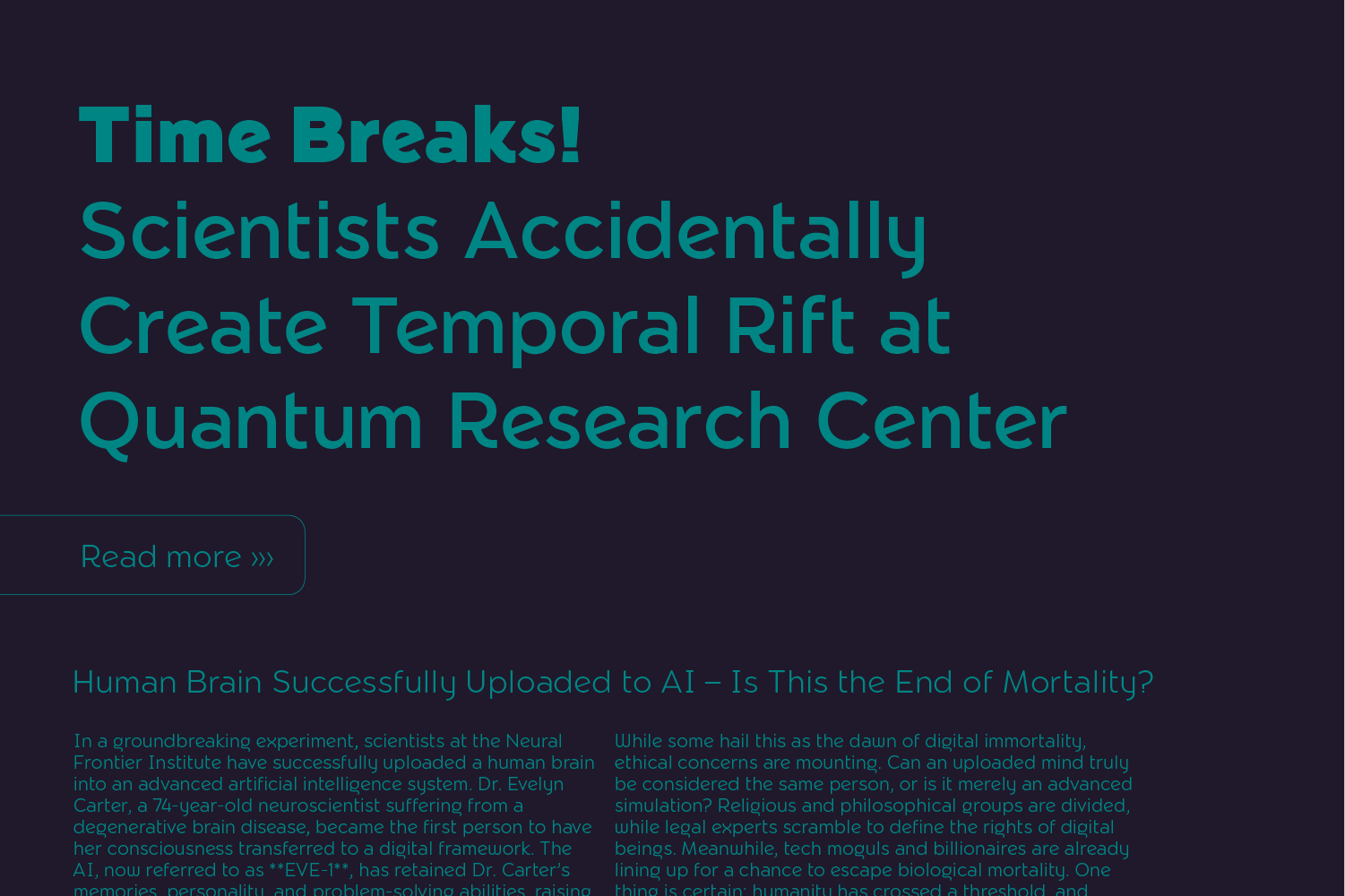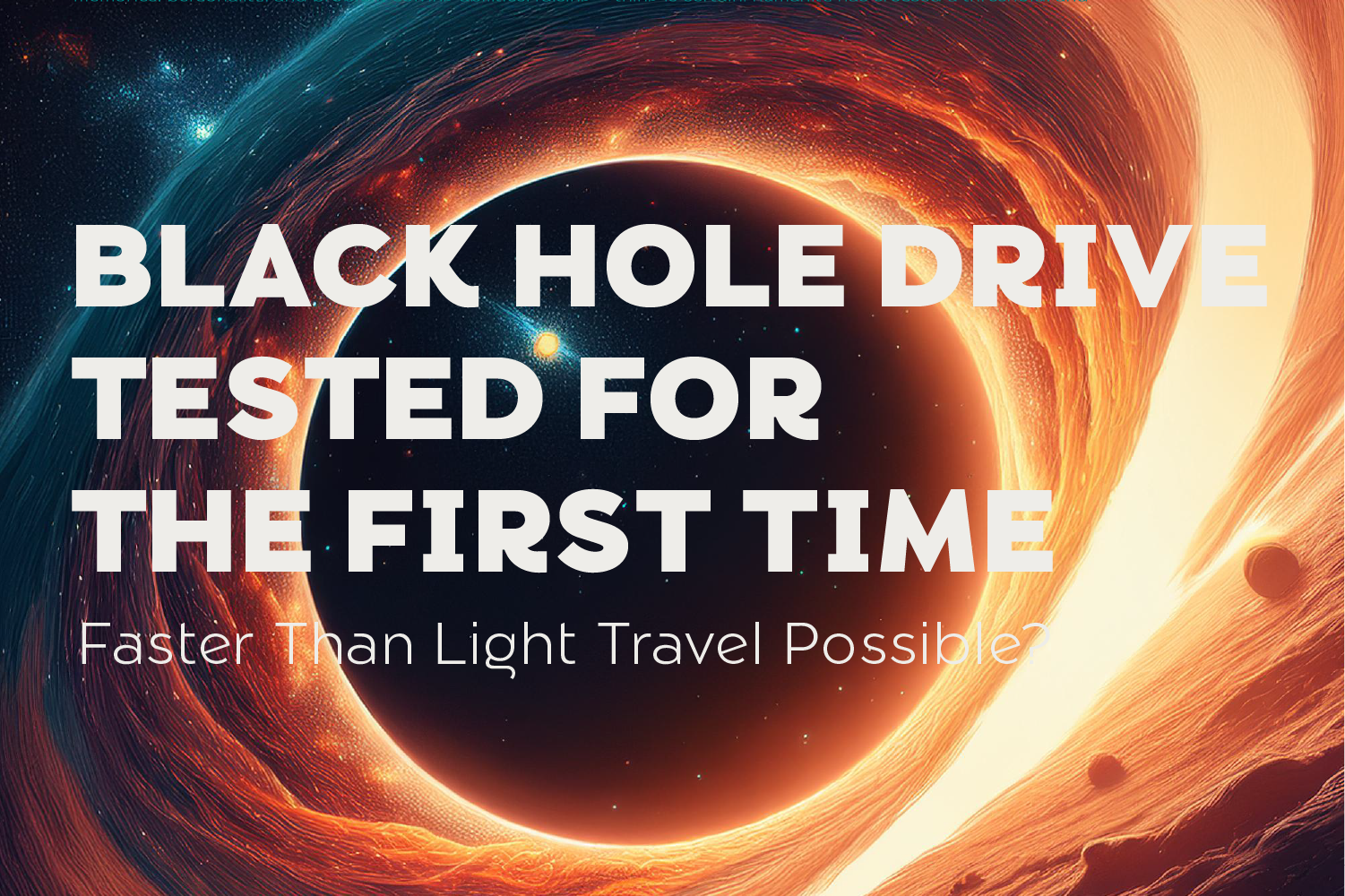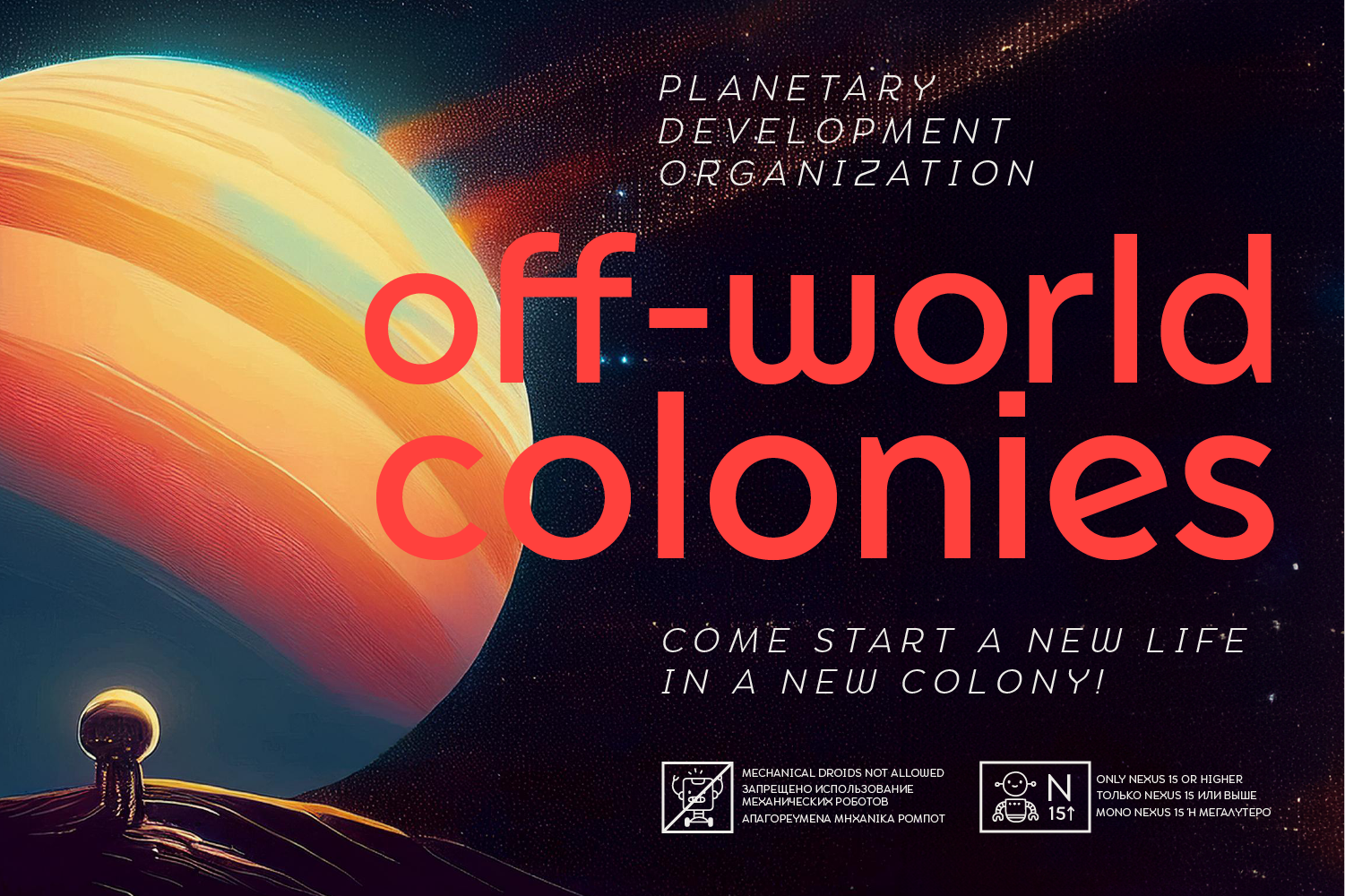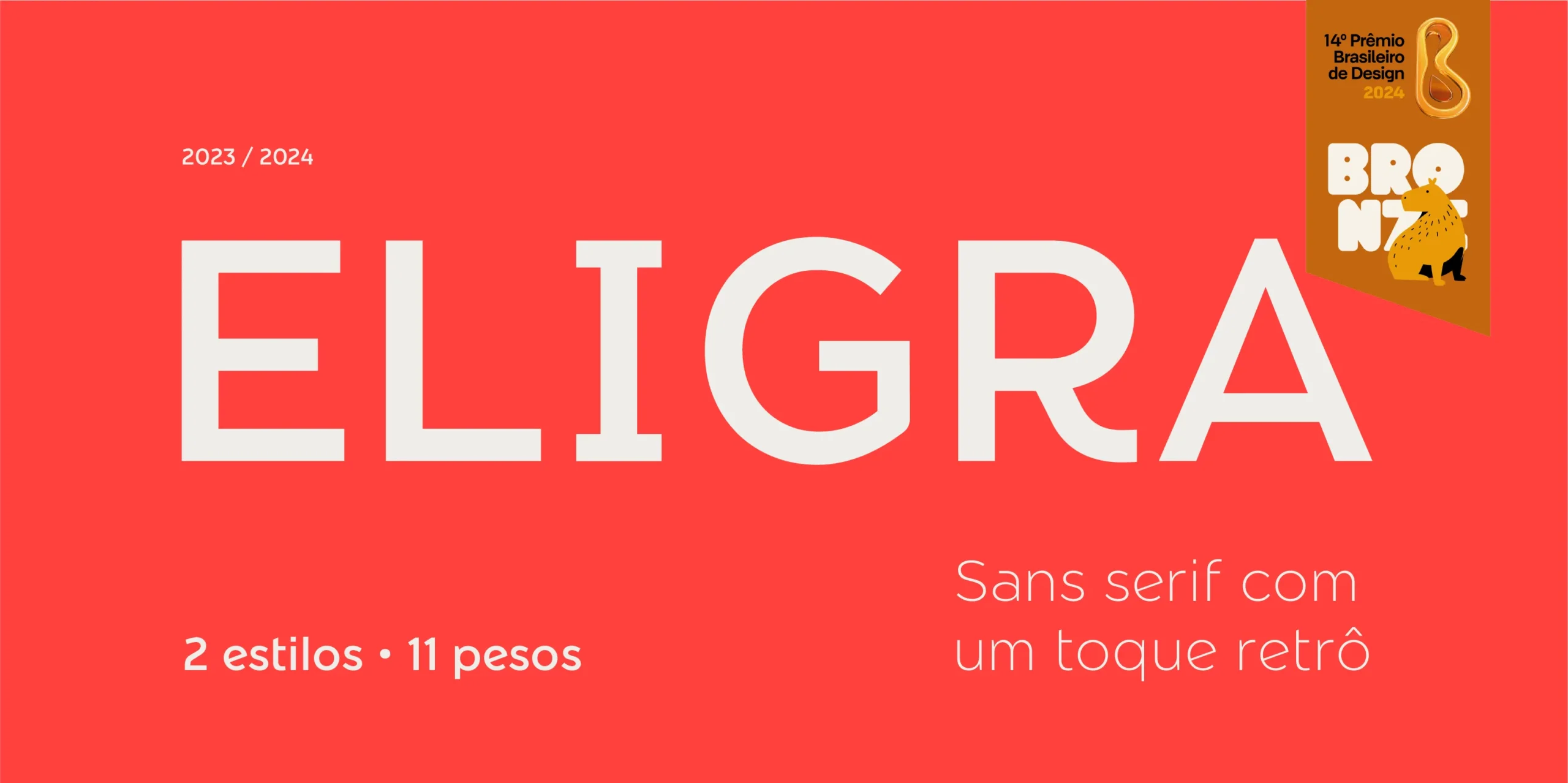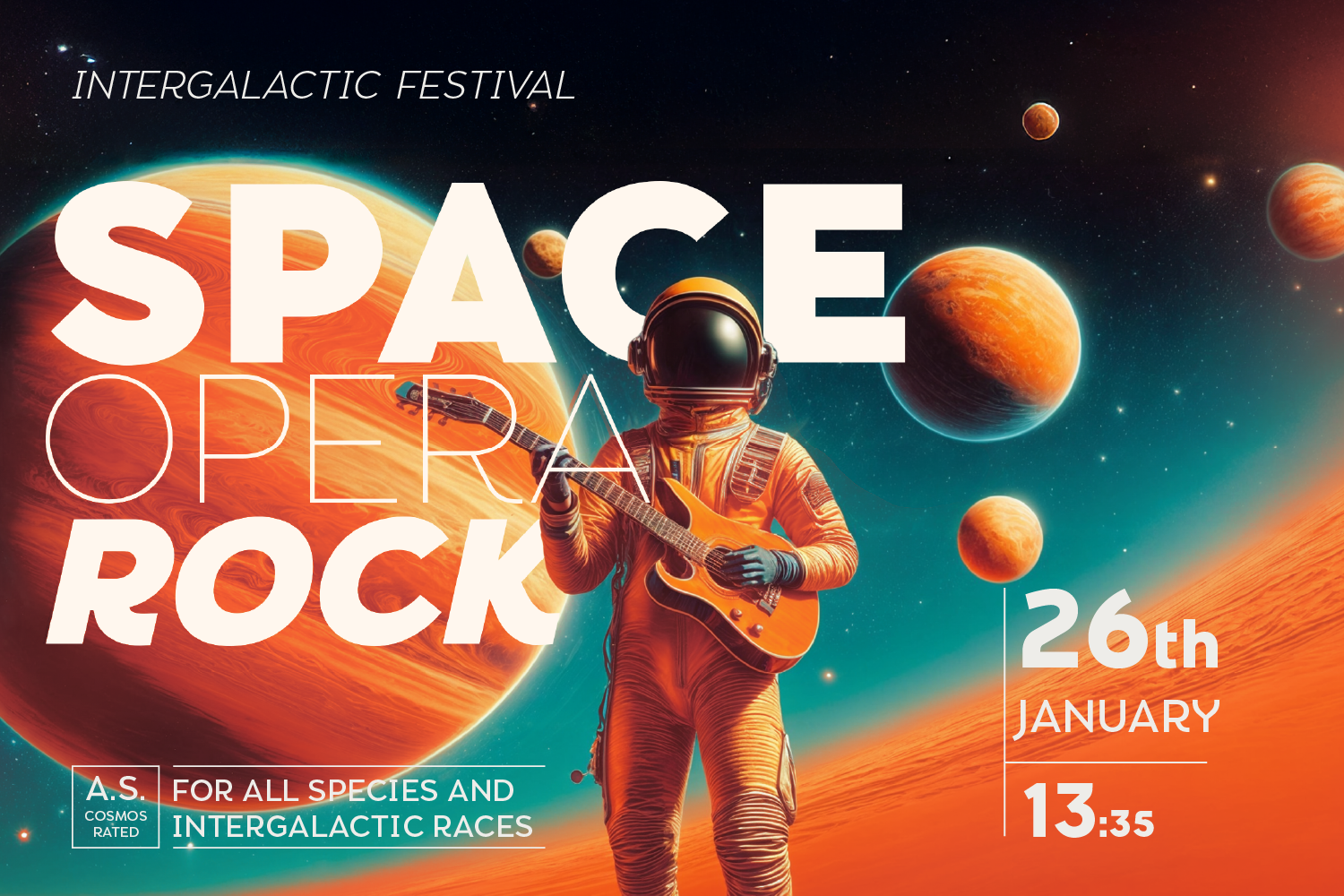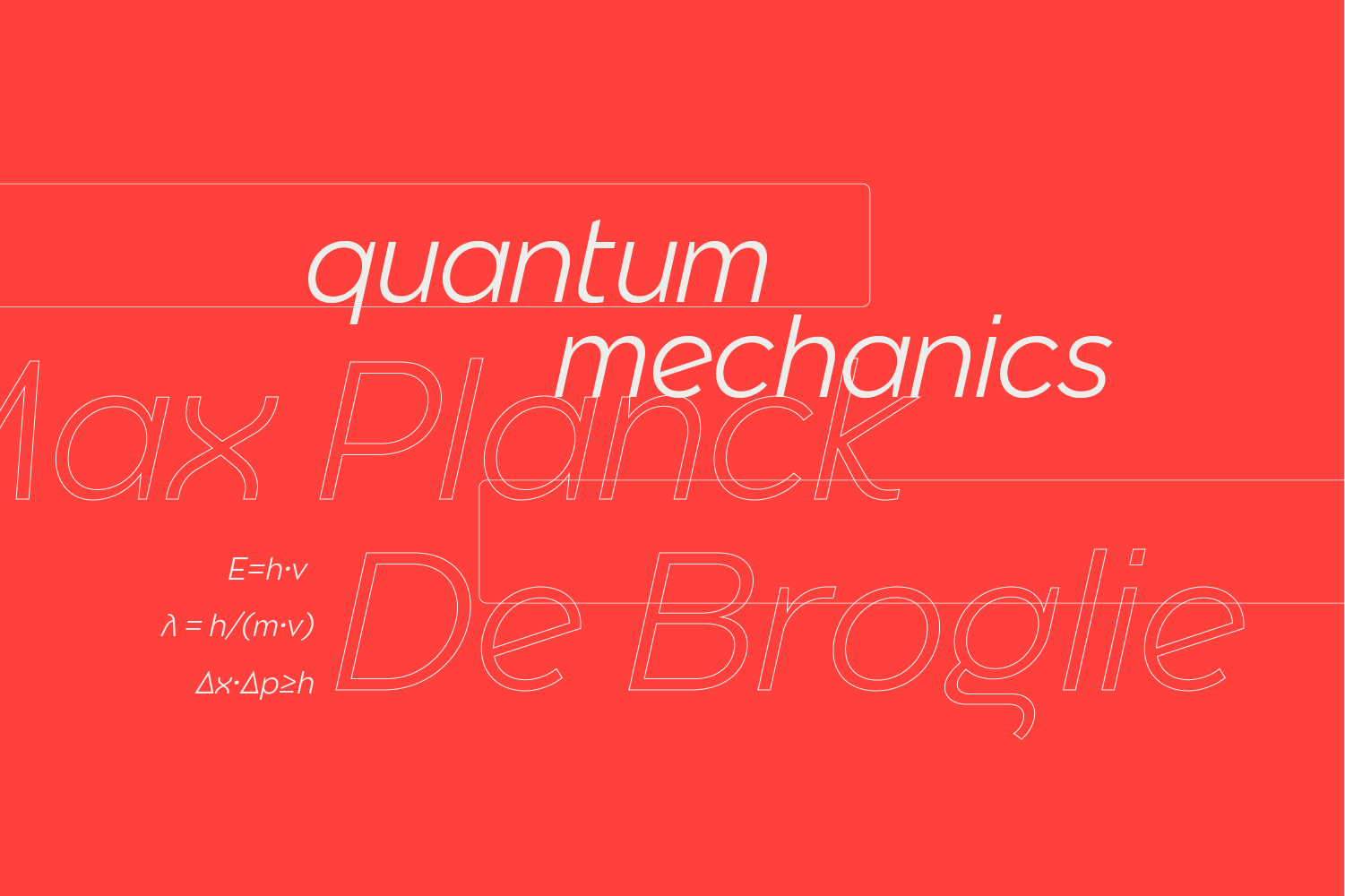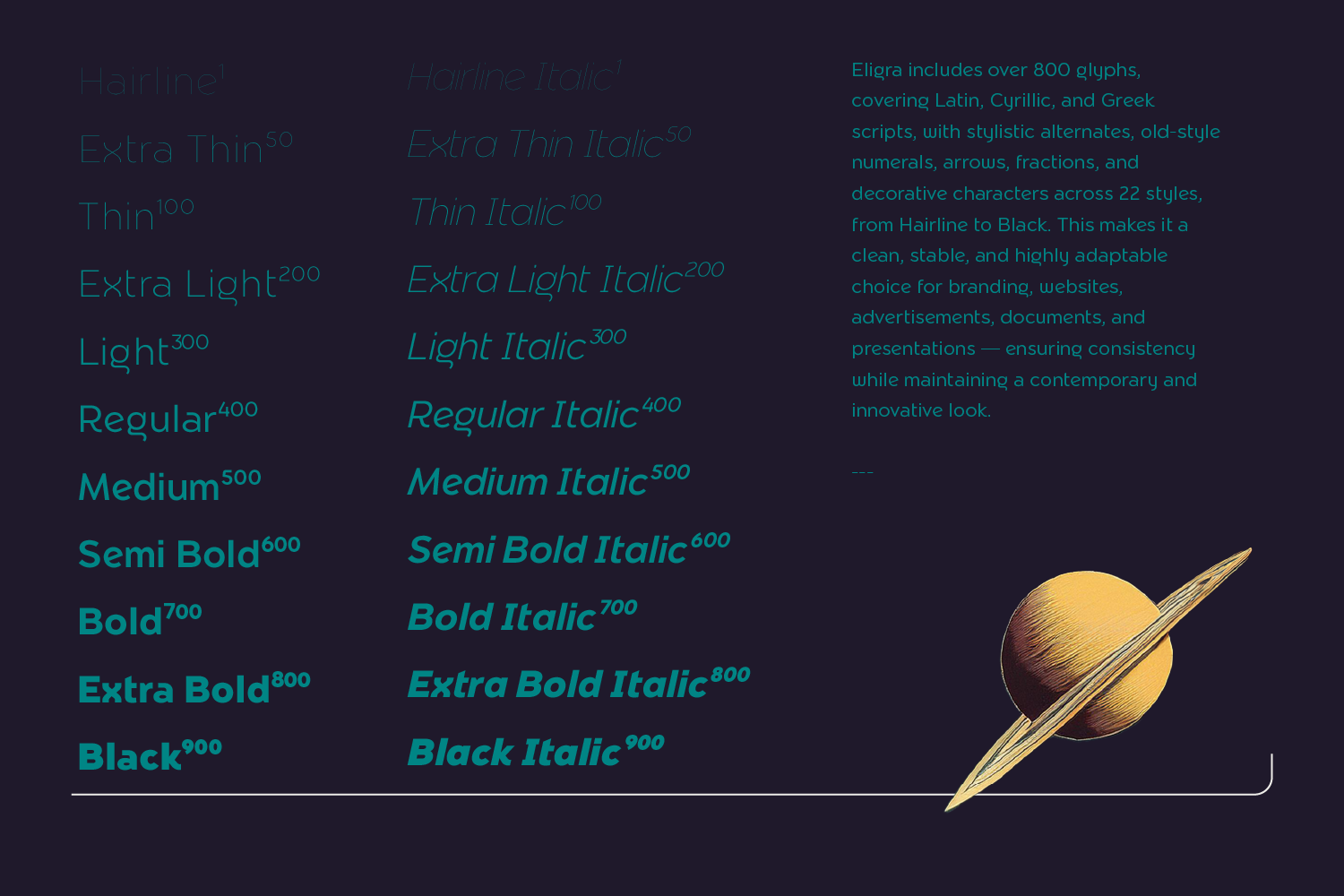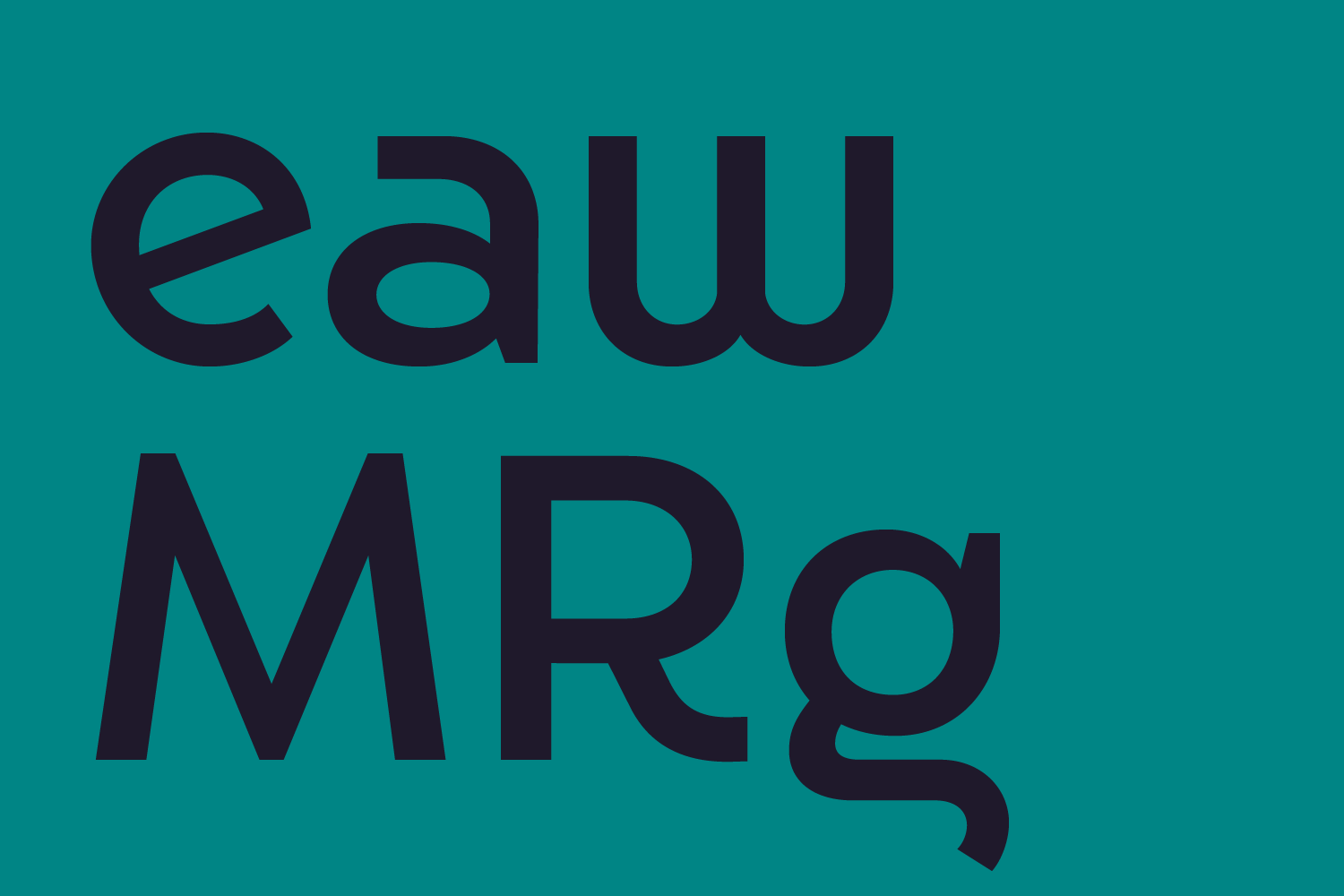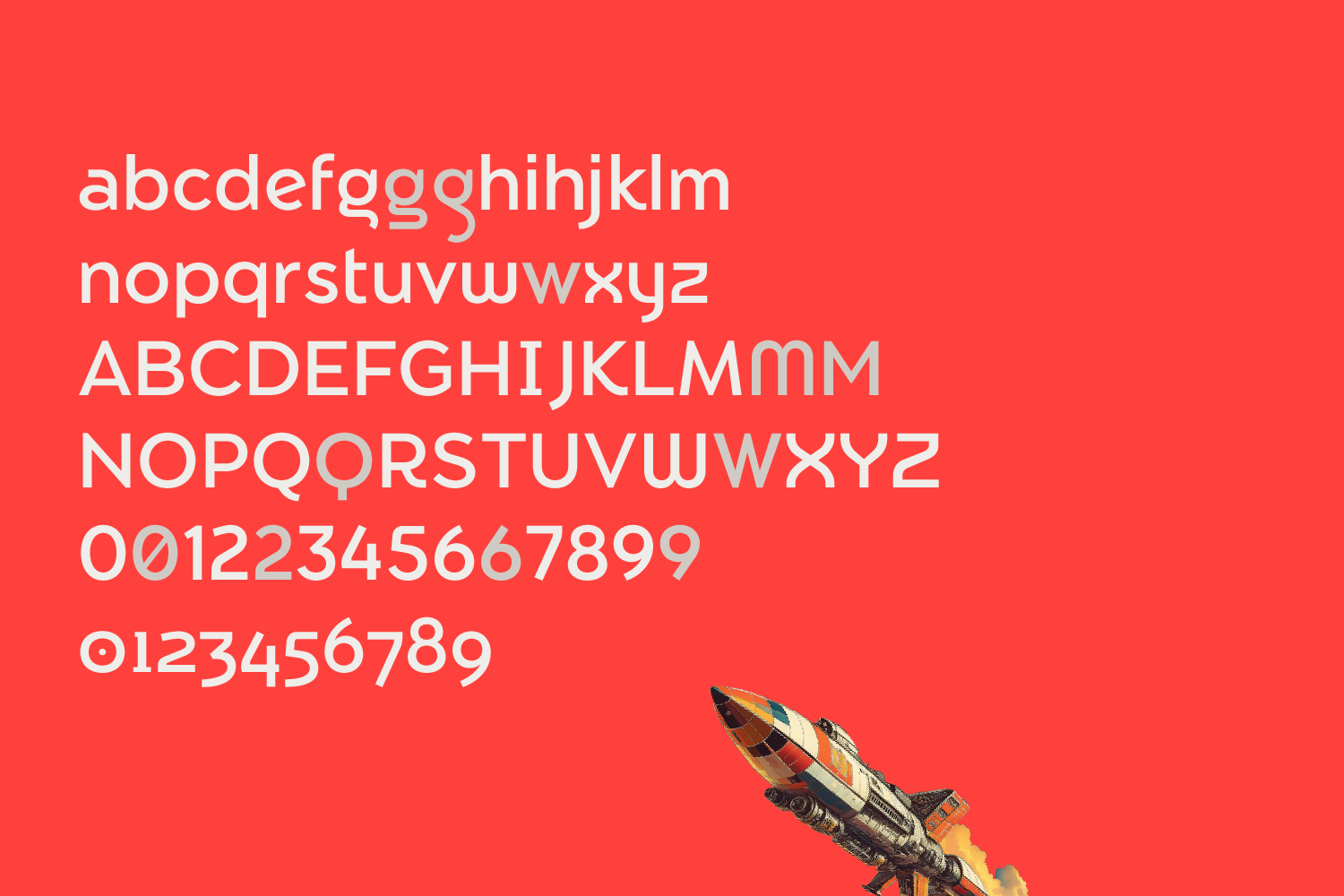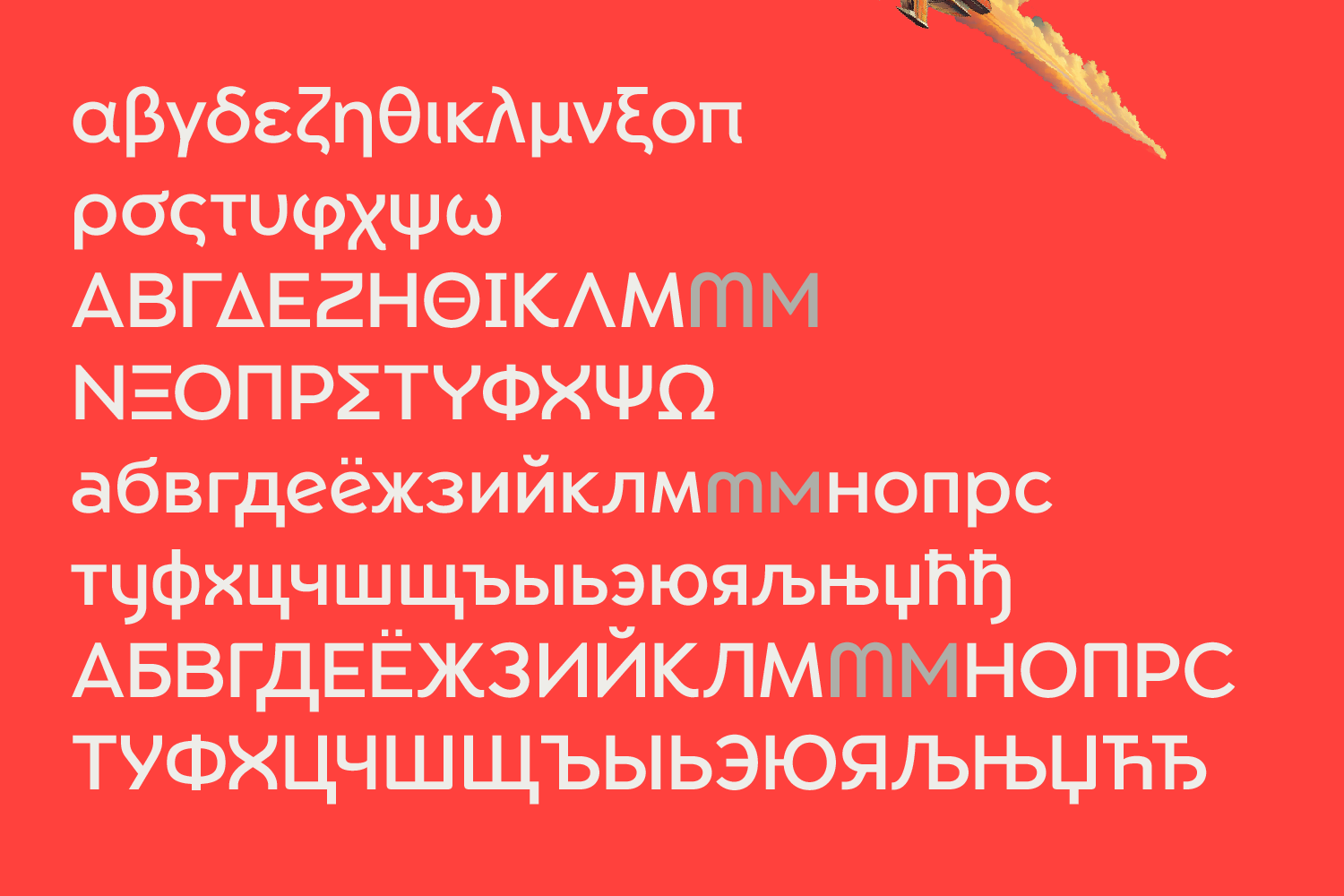
Eligra é uma família tipográfica sem serifa moderna e elegante, originalmente desenvolvida para uma marca pessoal e posteriormente expandida para uso comercial. Com estrutura geométrica e estética retrô-futurista, é inspirada em clássicos como Helvetica, Gotham e, principalmente, Universal, de Herbert Bayer.
Eligra é versátil e pode ser usada tanto como elemento de identidade em uma marca quanto em UI e títulos.
Foi ganhadora de Bronze em Tipografia – Craft For Design, no 14º Prêmio Brasileiro de Design 2024.